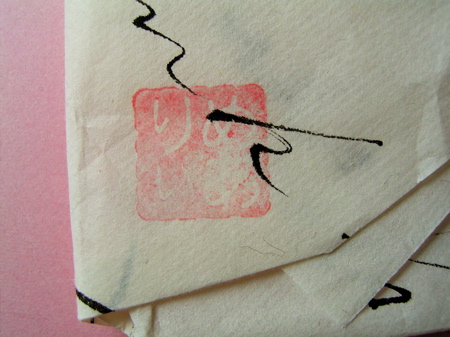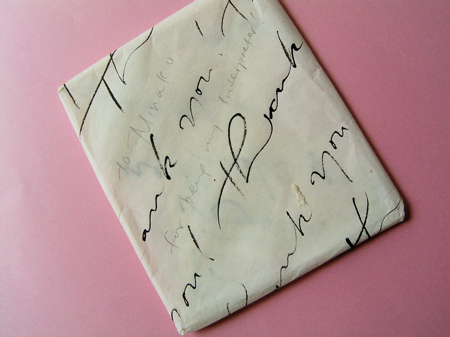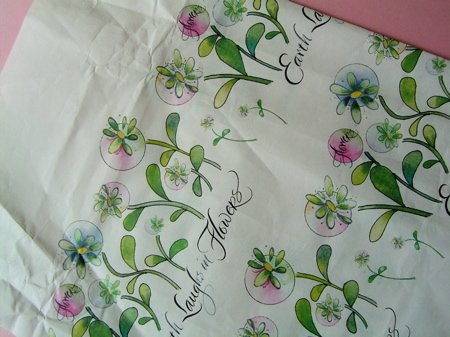
ラッピングペーパーとはんこ
きょうまで、鈴木泰子さんの個展が銀座伊東屋で開催されていますが、以前頂いたラピングペーパー(DMが包んでありました)、とても素敵で取っておいたのです。
おおきなサイズが印刷出来るプリンターを入手されてプリントしたものだそうです。うーん、そうか!ちょっと手間をかければこうして人を喜こばせる物が出来るのかもしれません。(でも、それにはもとのオリジナルのデザインが良くなくてはなりませぬ
)mojitor-hさんがとても得意のスキャン技とコピー技を使えば、予想以上に楽しいものが出来るかもしれません。
半紙に墨と筆でシンプルにThank youと繰り返し書いてあります。
中身がなくてこれだけ頂いても嬉しいかもー
これはイギリスのカリグラファー Mary Nobleさんから頂いた物です。嬉しいです!
封を開けようと裏を見てまたニンマリ。どなたかMary のために作って差し上げたのかしら?可愛い!可愛すぎる!このはんこ!
そう言えば昔カリグラファーのEwan Claytonに「遊庵」と書いたものを差し上げたことがありました。「ゆうあん」でも可愛いかったかもね。(でもちょっと、ゆうこりんみたいかも・・・?)
ひらがなのはんこは4文字だから形になるのかも。
日本人の女子の名前は3文字が多いからねぇ〜。いや、今時の名前は洗練されてるから、4文字も以外とあるのかもね〜。「さくらこ」とか、「かおるこ」とか?う〜ん、「こ」以外が付く4文字の名前ってないかしらん・・!?
源氏物語にはたくさんいますよね・・・夕霧、桐壺、空蝉などなど。